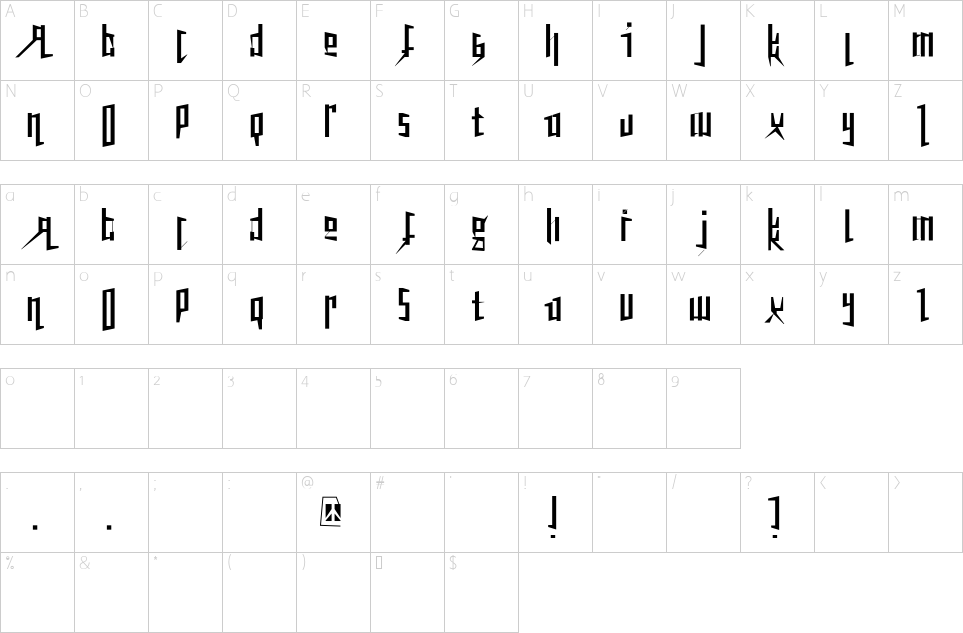
Peacetiqua é uma fonte elegante e sofisticada, perfeita para ambientes gráficos que procuram um equilíbrio harmonioso. Ela foi criada por Manfred Klein e é ideal para uso em projetos de design gráfico, desde editoriais de revistas até trabalhos de design editorial. Com um design minimalista e um conjunto completo de caracteres, Peacetiqua é a escolha perfeita para quem busca uma fonte que combine simplicidade com modernidade. Seja você um designer gráfico profissional ou um estudante, essa fonte gratuita é uma ótima adição a seu arsenal de recursos, com a facilidade de download tanto para sistemas Windows quanto para Mac.